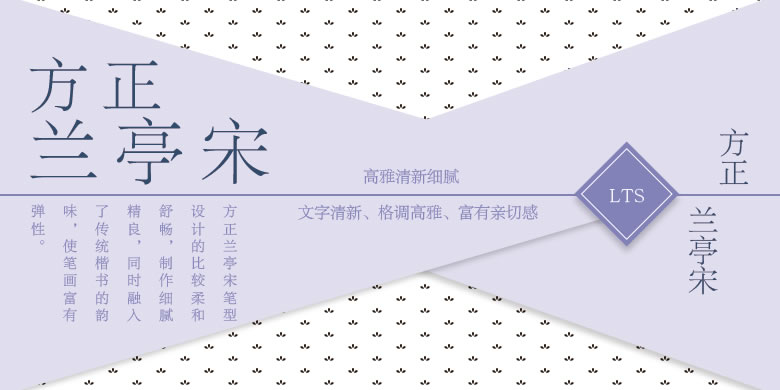
方正兰亭宋是针对新一代报纸正文设计的。这款字体制作细腻精良,笔形融入了传统楷书的韵味,舒畅而富有弹性,重心略高,字形清秀,格调高雅。由于报纸正文字体的笔画较细,在高速印刷时字体一些部分容易被弱化,因此特意加强了文字的顿挫,即笔画上的装饰角,给眼睛以适当的刺激,从而进一步提高阅读效果。这样的特征,可以防止排印小字号的文字时笔画端被弱化,使文字更清晰易读。同时,还进一步匀化了字白空间,文本灰度更为均衡,增加了阅读的舒适性。除了报纸,也适用于杂志、书籍等高精度印刷的媒介。